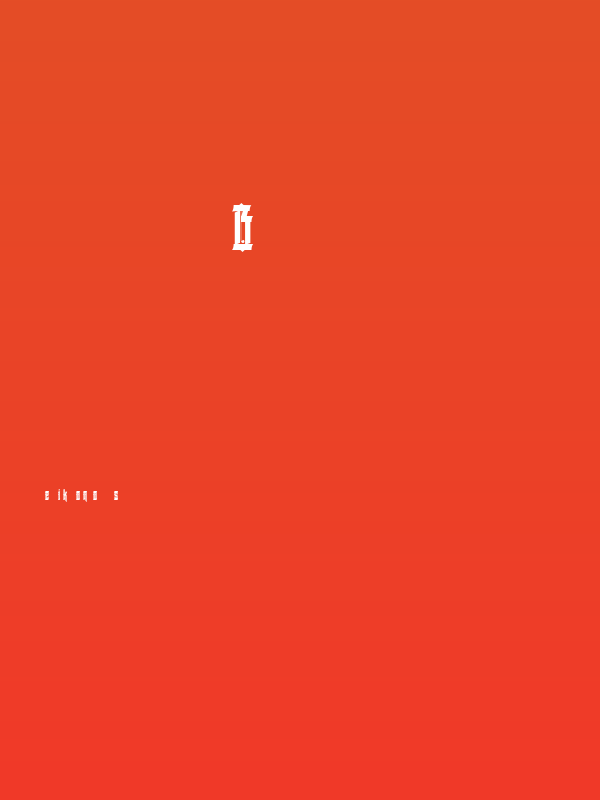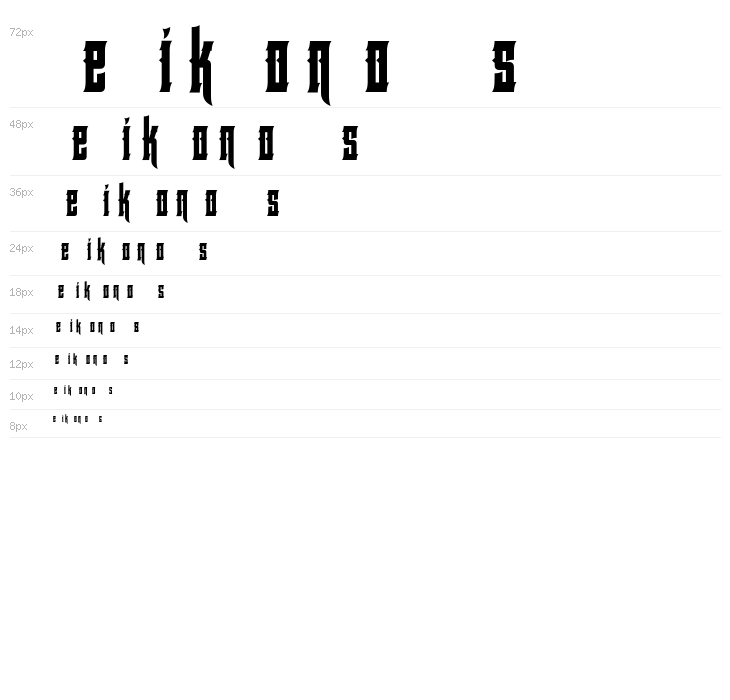
Basingstoke Font
✎ Gothic
| Kategorien | Gothic |
| Gesamtstil | Vintage |
| Anwendungsfall | Logos, Headlines, Posters |
| Vorgeschlagene Projekte | Ideal for projects requiring a historical or gothic theme, such as book covers, posters, or branding for events with a medieval or fantasy focus. |